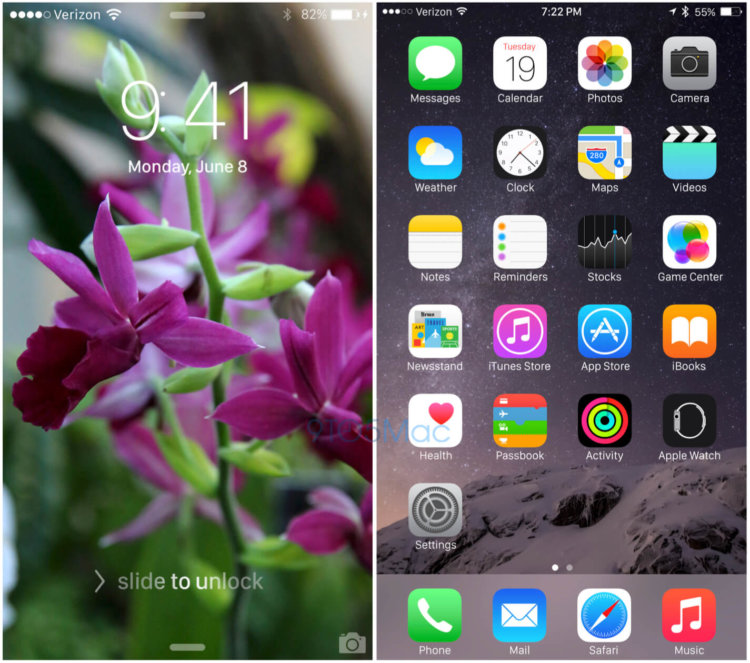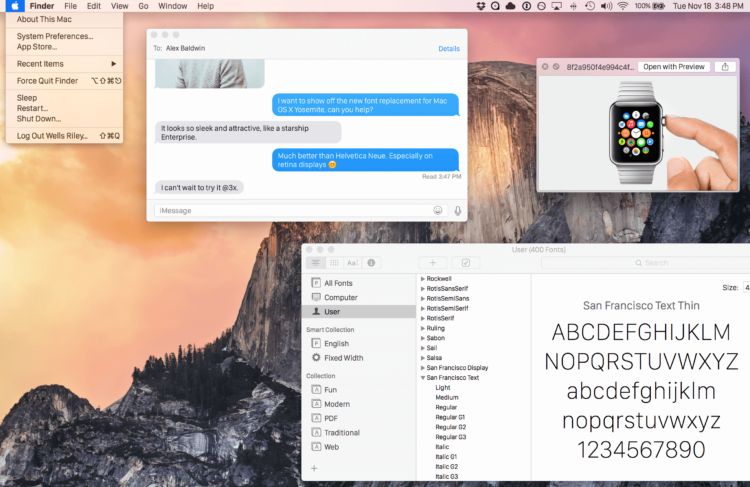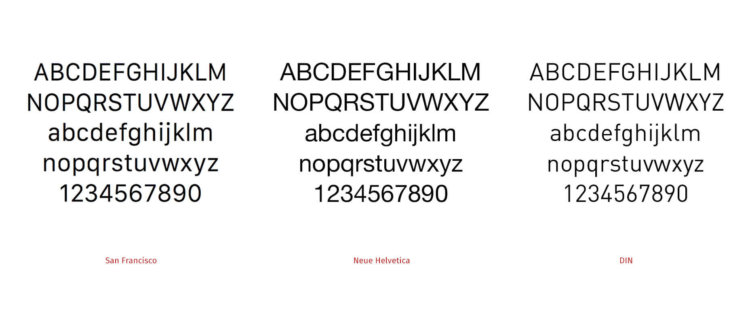
Apple планирует обновить шрифты в iOS 9 и OS X 10.11
Похоже, еще не разоблачили тех сотрудников Apple, которые активно делятся внутренней информацией с нашими коллегами из 9to5Mac, потому как они регулярно рассказывают нам новые подробности о будущих продуктах. На сей раз речь зашла об iOS 9 и OS X 10.11. Мы не ожидаем каких-либо серьезных изменений, однако согласно источнику 9to5Mac, какие-то изменения все же будут, и коснуться они интерфейса системы.
Мы уже привыкли к шрифту, который используется в iOS 7 и OS X Yosemite. Он называется Helvetica Neue и призван подчеркнуть чистоту линий. По всей видимости, он не сильно подходил для использования в Apple Watch с достаточно компактным дисплеем, поэтому для них был использован шрифт San Francisco. Именно шрифт San Francisco, согласно слухам, обновит внешний вид мобильной и настольной операционных систем от Apple.
Подобное решение, если Apple действительно на это решится, будет не просто принять как самой компании, так и разработчикам. Переработка всех деталей интерфейса и приложений таким образом, чтобы новый шрифт хорошо смотрелся при любом размере, займет немало времени и сил. Тем не менее, некоторые сотрудники рассказали, что еще в марте сборки новых ОС работали с новым шрифтом. Известно также, что некоторые разработчики сторонних приложений уже обновили шрифты, взглянув на клавиши нового MacBook.
Решится ли Apple на замену шрифта в iOS и OS X мы вероятно узнаем 8 июня, в день старта WWDC 2015. Возможно компания все же отложит эти планы на будущее, хотя бы потому, что система должна выглядеть однородно на всех языках, а шрифт San Francisco о русском языке, похоже, не наслышан.